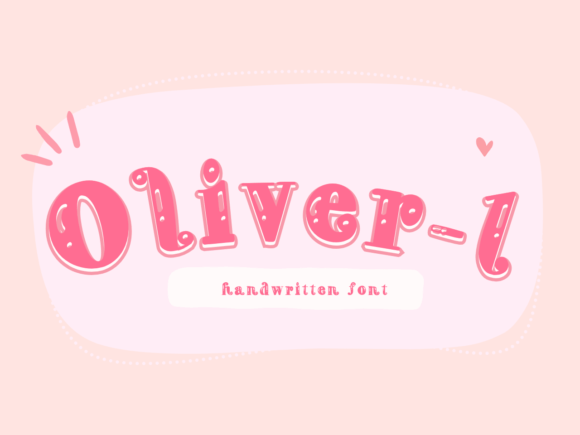
Oliver-1
Пошук відповідних елементів дизайну може бути складним, але Oliver-1 пропонує виняткову колекцію, яка миттєво покращить вашу роботу.
Незалежно від того, чи створюєте ви продукти POD (друк на вимогу), весільні запрошення або графіку для соціальних мереж, Oliver-1 стане ідеальним вибором.